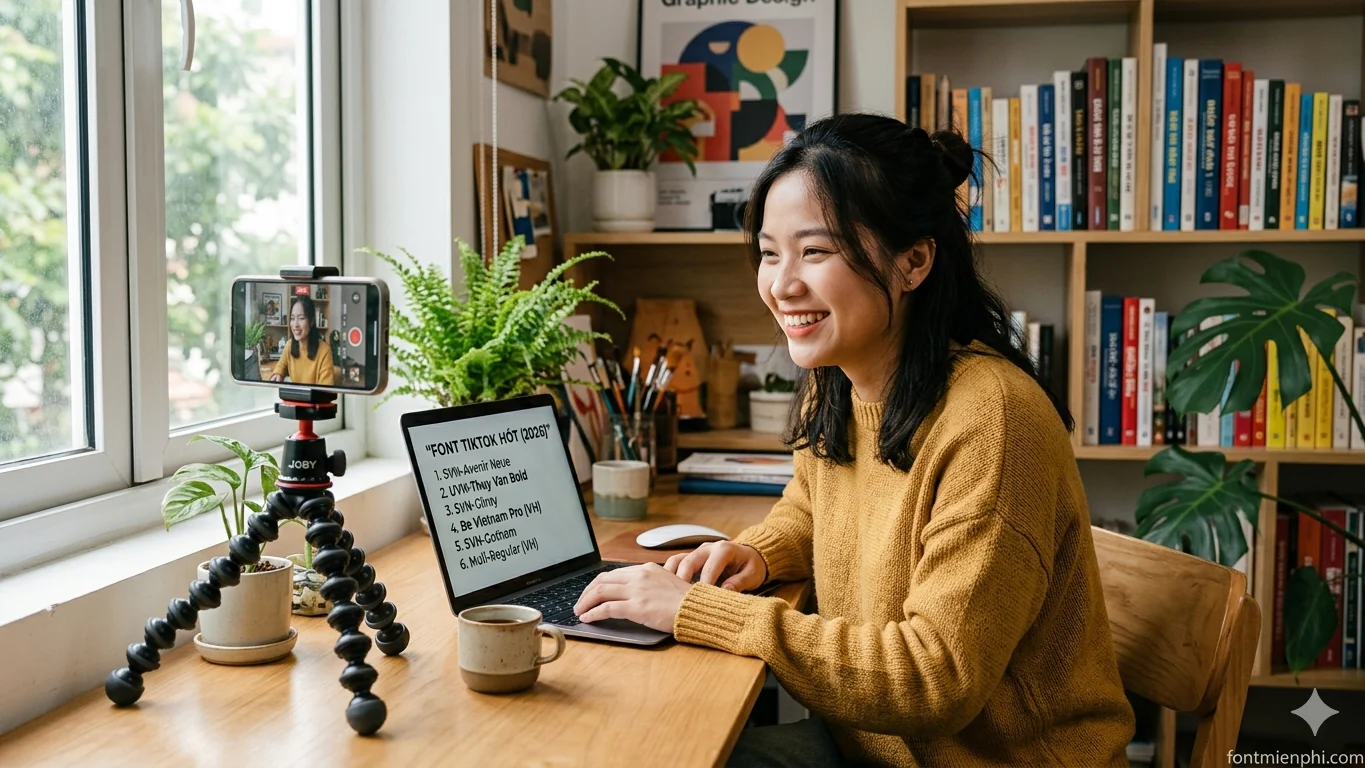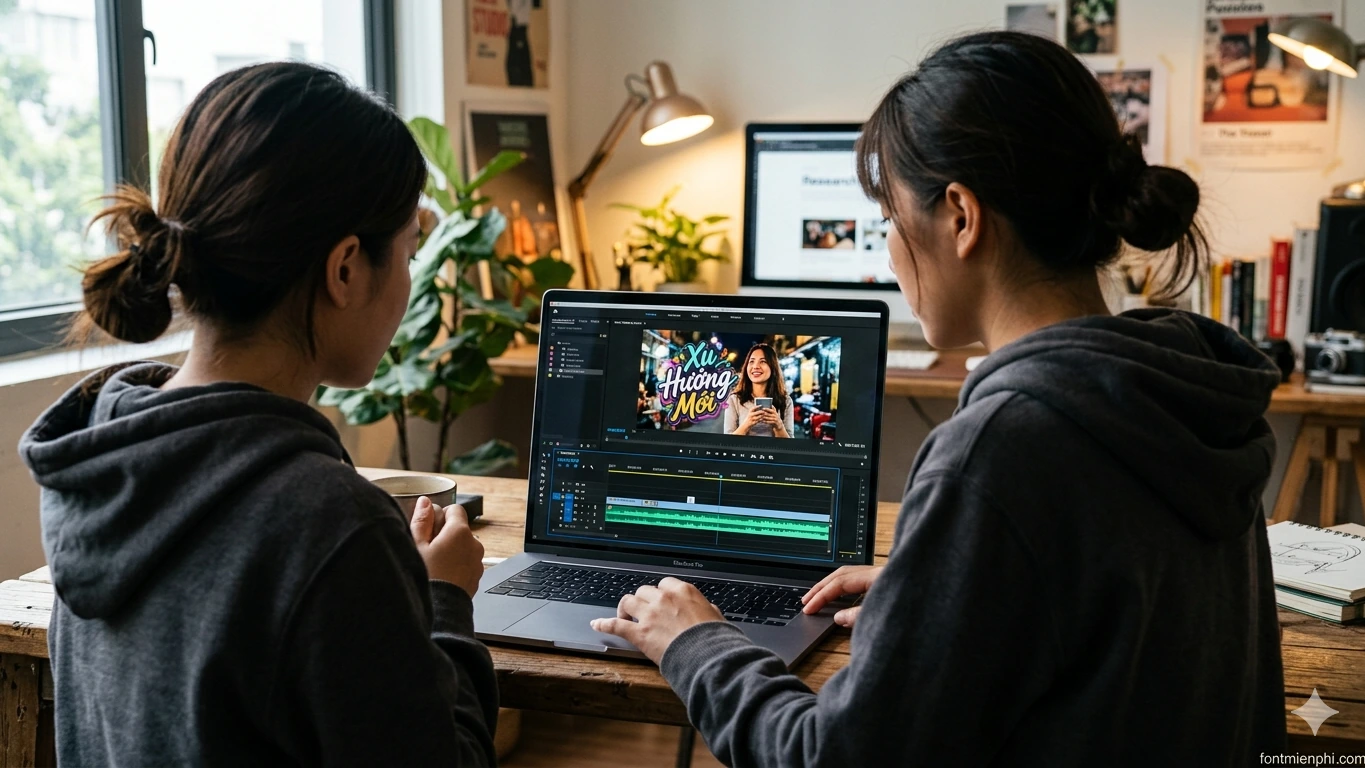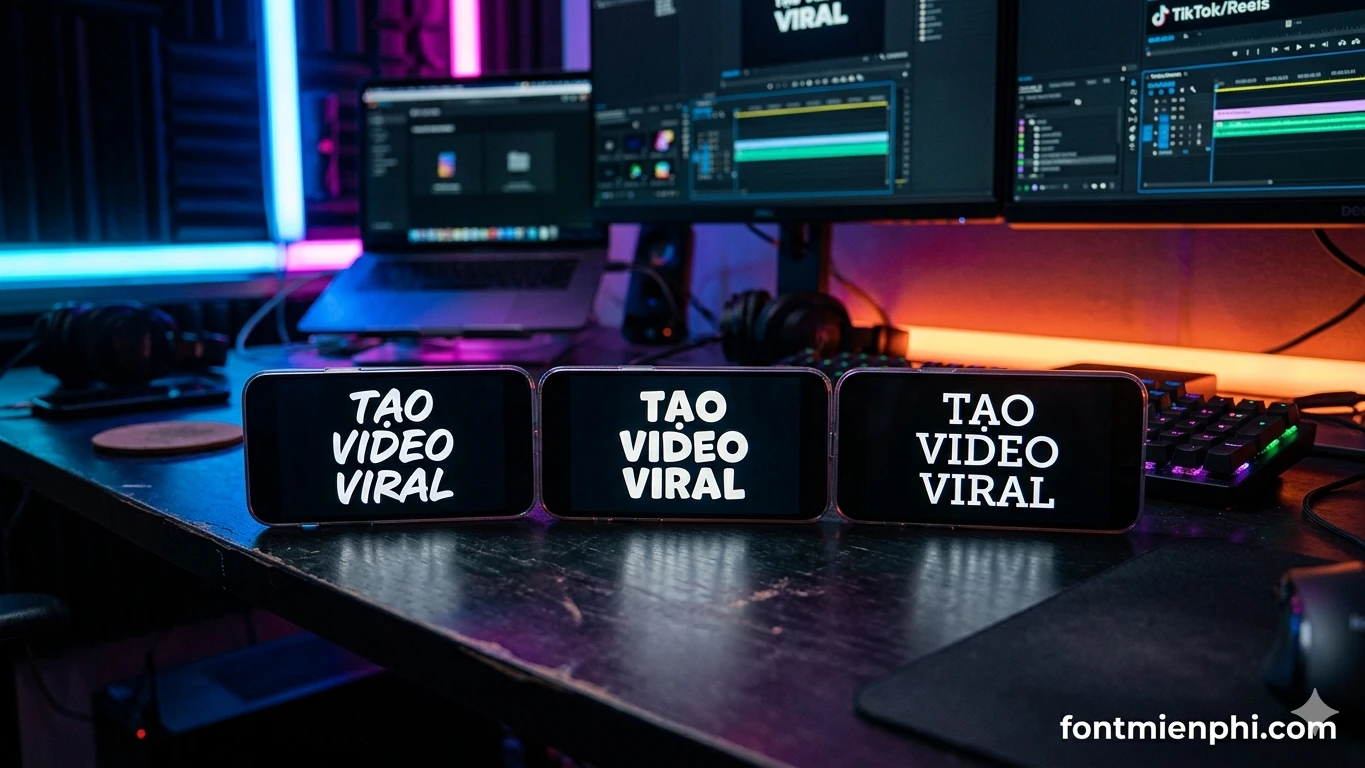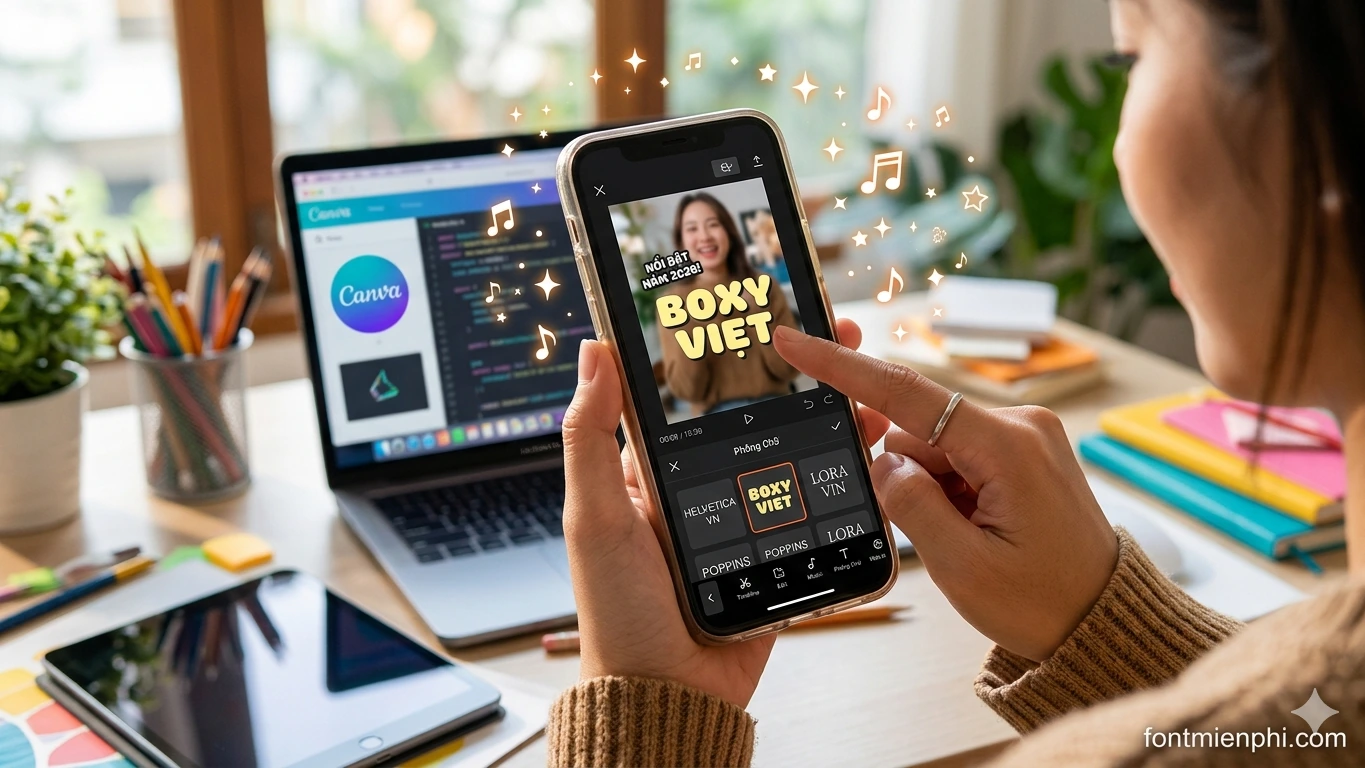
Top Font Việt Hóa Dùng Cho Video TikTok Reels Viral 2026
Trong kỷ nguyên sáng tạo video ngắn năm 2026, font chữ không chỉ là công cụ truyền tải thông tin mà còn là yếu tố nhận diện thương hiệu cá nhân mạnh mẽ. Bài viết này sẽ tổng hợp những bộ font Việt hóa dẫn đầu xu hướng trên TikTok và Reels, giúp video của bạn thu hút thị giác, tối ưu hóa trải nghiệm người dùng và gia tăng tỷ lệ chuyển đổi hiệu quả.
Top Font Việt Hóa Dùng Cho Video TikTok Reels Viral 2026
Việc lựa chọn phông chữ phù hợp cho video ngắn hiện nay đòi hỏi sự kết hợp giữa tính thẩm mỹ hiện đại và khả năng đọc nhanh trong điều kiện người xem lướt qua màn hình liên tục. Một font chữ tốt phải đảm bảo không bị lỗi dấu tiếng Việt, có độ tương phản cao với nền và phản ánh đúng tinh thần của nội dung.
Tại sao font chữ quyết định sự thành công của video ngắn năm 2026
Trong bối cảnh thuật toán của các nền tảng như TikTok và Facebook Reels ngày càng ưu tiên giữ chân người dùng, phụ đề (captions) đóng vai trò sống còn. Khoảng 80% người dùng xem video ở chế độ tắt âm thanh trong những giây đầu tiên. Do đó, kiểu chữ đóng vai trò là giọng nói thị giác của bạn.
Tăng cường khả năng tiếp cận: Người xem có thể hiểu nội dung ngay cả khi đang ở nơi công cộng không tiện bật loa.
Tạo điểm nhấn thị giác: Những từ khóa quan trọng được định dạng bằng font chữ ấn tượng sẽ kích thích não bộ ghi nhớ lâu hơn.
Định hình phong cách: Một video về công nghệ cần font chữ không chân (sans-serif) cứng cáp, trong khi video về đời sống (lifestyle) lại ưu tiên những font chữ mềm mại hơn.
Xu hướng thiết kế chữ cho video năm 2026
Năm 2026 đánh dấu sự lên ngôi của các phong cách thiết kế chữ mang tính tối giản nhưng có chiều sâu. Người dùng không còn ưa chuộng những font chữ quá rườm rà, thay vào đó là những bộ font có đường nét dứt khoát hoặc mang hơi hướng hoài cổ (retro) được làm mới.
Phong cách Kinetic Typography
Đây là xu hướng chuyển động chữ theo nhịp điệu âm nhạc. Để làm được điều này, các nhà sáng tạo cần những font chữ có độ dày (weight) đa dạng từ cực mỏng đến cực dày để tạo sự tương phản khi chuyển cảnh.
Phong cách Y2K và Futuristic
Sự trở lại của thập niên 2000 kết hợp với yếu tố tương lai tạo nên một làn sóng mới. Các font chữ có hình dáng lạ mắt, bo góc hoặc kéo dài đang trở thành tâm điểm trên các video xu hướng của giới trẻ.
Danh sách các bộ font Việt hóa không thể bỏ qua cho TikTok và Reels
Dưới đây là những gợi ý chi tiết về các bộ font đã được Việt hóa hoàn chỉnh, đảm bảo không lỗi font khi gõ các ký tự có dấu phức tạp như ế, ố, hẻ, hũ.
Nhóm font chữ không chân hiện đại (Sans-serif)
Đây là nhóm font phổ biến nhất vì tính dễ đọc và sự chuyên nghiệp.
Montserrat Việt hóa: Một huyền thoại chưa bao giờ lỗi mốt. Với hơn 18 biến thể khác nhau, Montserrat phù hợp cho cả tiêu đề chính lẫn phụ đề chạy dọc video.
Be Vietnam Pro: Một bộ font được thiết kế bởi người Việt, tối ưu hoàn hảo cho các dấu câu tiếng Việt, mang lại cảm giác cân đối và thanh lịch.
Lexend: Được thiết kế đặc biệt để cải thiện tốc độ đọc, rất phù hợp cho những video có lượng văn bản lớn hoặc các video dạng kiến thức, tin tức.
Archivo Black: Một font chữ cực đậm, tạo sức nặng cho những câu nói mang tính khẳng định hoặc các tiêu đề gây sốc (clickbait).
Nhóm font chữ viết tay và nghệ thuật (Script & Display)
Nhóm này thường được dùng để trang trí hoặc làm các câu trích dẫn (quotes) ngắn để tạo cảm xúc.
SVN-Haptic Script: Mang lại cảm giác gần gũi, thủ công, rất thích hợp cho các vlog nấu ăn hoặc chia sẻ tâm sự đời thường.
UTM Alexander: Một font chữ mềm mại, có độ bay bổng nhất định nhưng vẫn giữ được sự rõ ràng của mặt chữ.
Iciel Koni Black: Font chữ mang phong cách hoạt hình, vui nhộn, thường được các nhà sáng tạo nội dung hài hước sử dụng để tăng tính giải trí.
Nhóm font chữ mang phong cách Retro và Vintage
Sự hoài cổ luôn có chỗ đứng vững chắc trong lòng khán giả, đặc biệt là các video kể chuyện (storytelling).
SVN-Vesterbro: Sự kết hợp giữa nét cổ điển và hơi thở đương đại, tạo nên sự sang trọng cho các video về thời trang và kiến trúc.
Classico Việt hóa: Mang phong cách của những poster điện ảnh cũ, giúp video của bạn trông giống như một tác phẩm nghệ thuật hơn là một clip ngắn thông thường.
Cách phối hợp font chữ để tối ưu hóa tỷ lệ giữ chân người xem
Sử dụng quá nhiều font chữ trong một video có thể gây rối mắt, nhưng chỉ dùng một font duy nhất đôi khi lại gây nhàm chán. Quy tắc vàng trong năm 2026 là sự kết hợp tối đa 2 đến 3 kiểu chữ.
Kết hợp font tiêu đề và font phụ đề
Bạn nên chọn một font chữ đậm, có cá tính mạnh cho các từ khóa chính và một font chữ đơn giản, dễ đọc cho phần nội dung chi tiết.
Ví dụ: Sử dụng Archivo Black cho tiêu đề chính để thu hút sự chú ý và Montserrat cho phần phụ đề bên dưới.
Sử dụng màu sắc và hiệu ứng đổ bóng
Các bộ font như SVN, UTM hay Iciel sẽ tiếp tục được cập nhật để phục vụ nhu cầu ngày càng cao của người dùng Việt. Sự đa dạng trong lựa chọn giúp các video từ dạng review sản phẩm, vlog du lịch đến các video chia sẻ kiến thức chuyên sâu đều có thể tìm thấy tiếng nói riêng thông qua những nét chữ được chăm chút kỹ lưỡng. Việc duy trì sự đồng nhất trong cách sử dụng font chữ qua từng video cũng góp phần xây dựng lòng tin và sự nhận diện từ phía khán giả, giúp kênh của bạn phát triển bền vững hơn trên các nền tảng mạng xã hội.